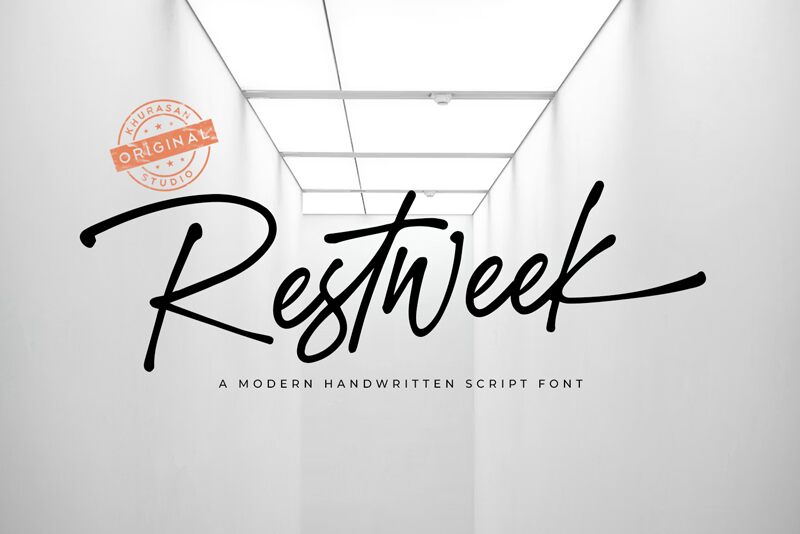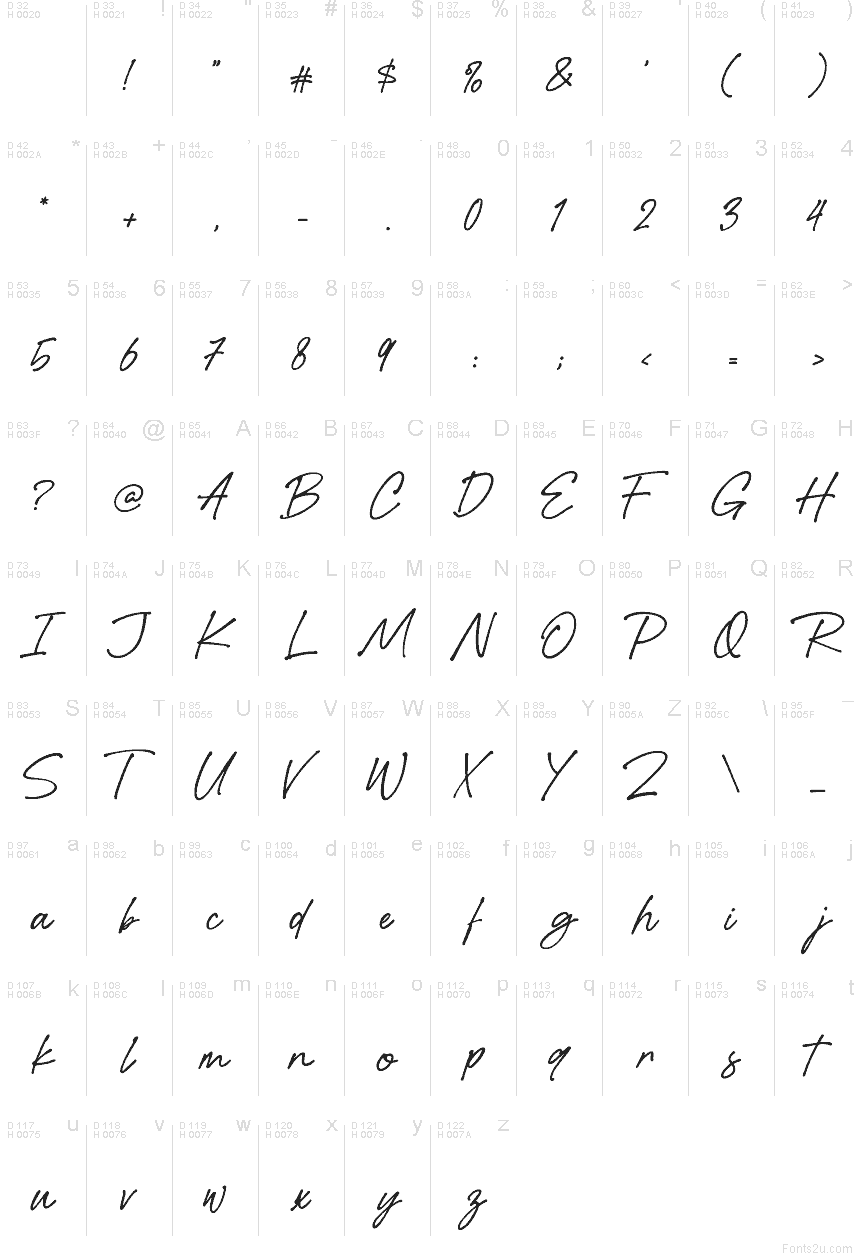
Restweek من Khurasan هو خط مجاني مكتوب بخط اليد يتميز بضربات سريعة وانسيابية وإيقاع طبيعي يشبه التوقيع. تعطي الزخرفة الطويلة في البداية نبرة مميزة، بينما يحافظ باقي الحروف على ميل غير رسمي وإيقاع متذبذب قليلاً، مما يمنح شعوراً بأنه كُتب بحركة واحدة واثقة.
تمنح هذه الديناميكية النصوص القصيرة حضوراً قوياً، فهي مثالية لمنشورات وسائل التواصل الاجتماعي، وتصاميم الاقتباسات، وملصقات التغليف، وبطاقات المعايدة، والعناوين بأسلوب الشعار. يبرز جمال هذا الخط حيث تظهر الخطوط المرسومة بوضوح، خاصة في العلامات التجارية أو بطاقات الدعوة التي تستفيد من امتدادات الأحرف والتدفق العفوي لخط اليد.